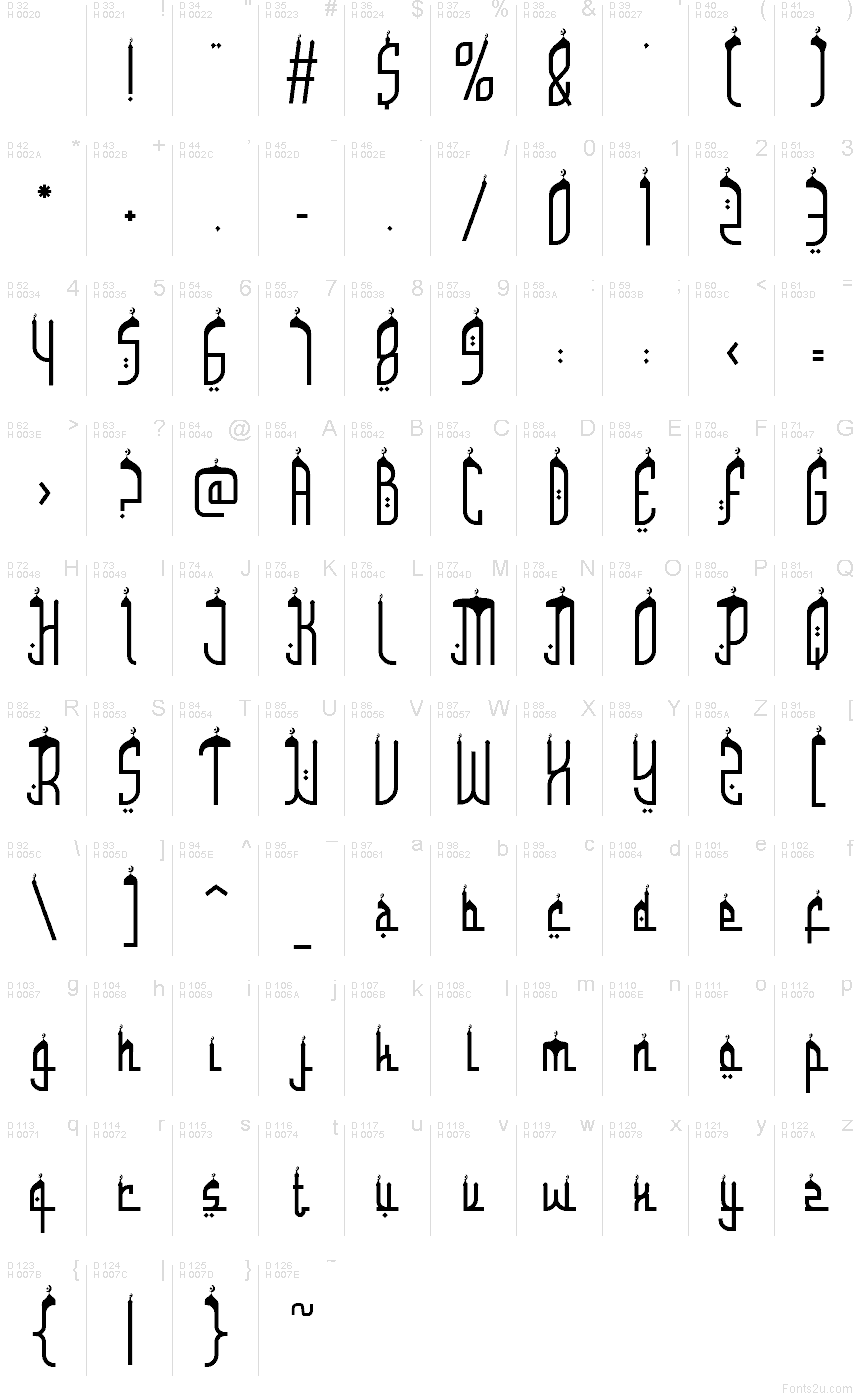
Nashir Nectar One od Putracetol Studio je bezplatné arabské písmo typu display, které definují vysoké iniciály připomínající mešity, akcenty v podobě půlměsíce a silueta evokující architektonické nápisy. Opakující se kupolovité vrcholky a vertikály podobné minaretům dodávají písmenům ceremoniální nádech, takže design vynikne spíše jako tematické titulek než jako neutrální hlavní text.
Tento charakter se skvěle hodí na plakáty k ramadánu, přání k svátku Eid, branding restaurací, akční bannery a obaly na datle, sladkosti nebo koření. Nejvíce vynikne v krátkých titulech, kde kopulovité vrcholy a detaily půlměsíců mohou orámovat rozvržení a okamžitě navodit arabský či islámský vizuální kontext.